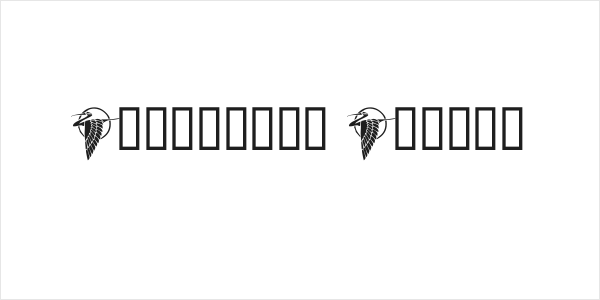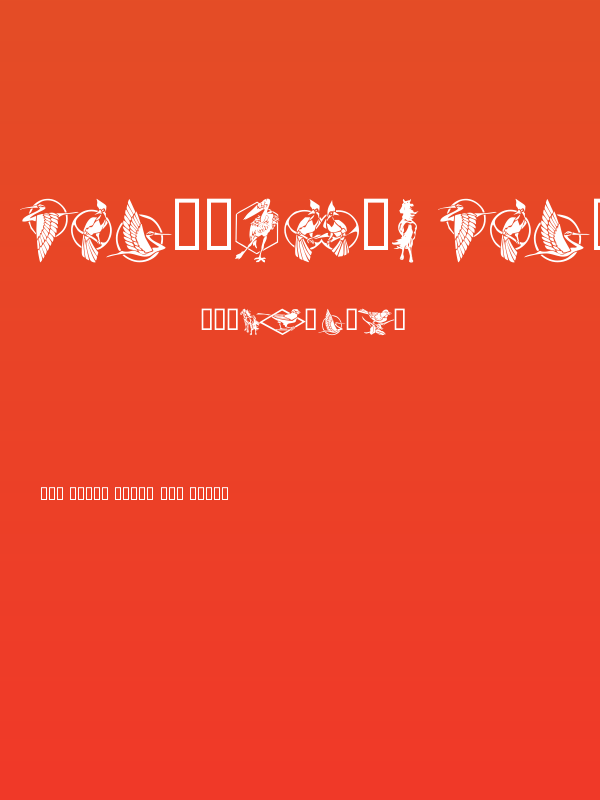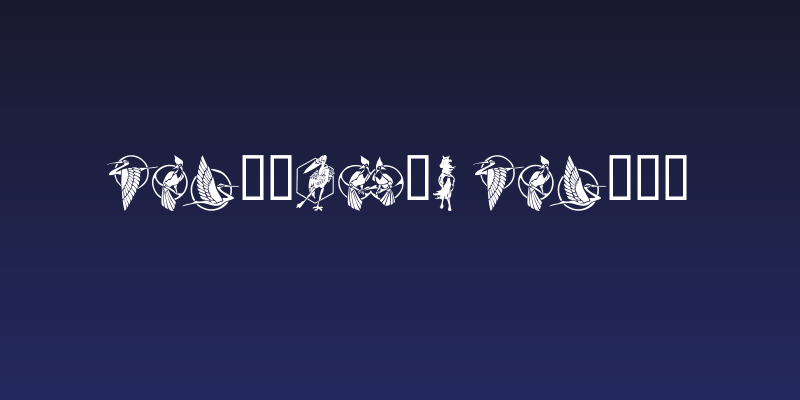
Beautiful Beasts Font
| Gesamtstil | Decorative, Fantasy, Artistic |
| Anwendungsfall | Logos, Headlines, Decorative elements |
| Vorgeschlagene Projekte | Book covers, fantasy posters, greeting cards, themed invitations, branding for pet or wildlife organizations. |